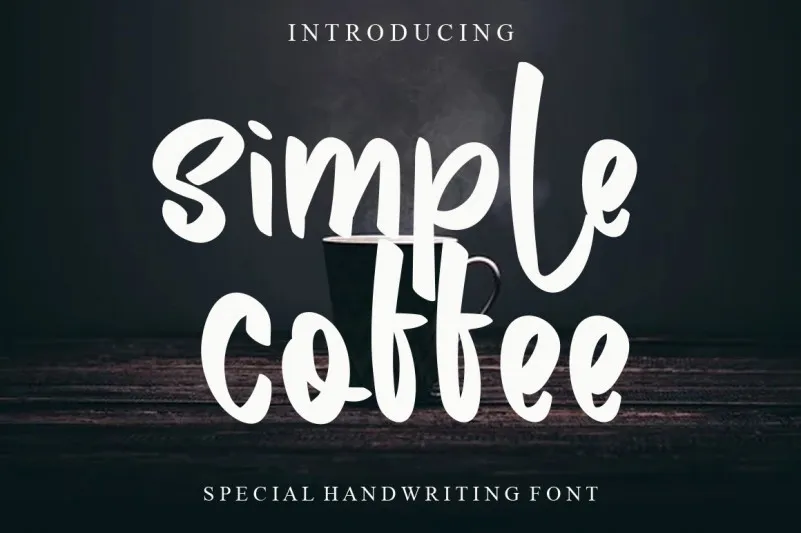
Esta é uma fonte a mão escrevendo, desenhada para designers que procuram algo fresco e divertido. Com um visual elegante e cíntica, ela promete dar seu projeto um toque único e moderno. Ideal para aqueles projetos criativos e inovadores onde você deseja destacar sua identidade visual com estilo. Composta por letras de uma escrita cursiva, essa fonte é perfeita para quem quer imprimir um tom pessoal e divertido em seus materiais digitais. Seja em postagens no Instagram ou cards personalizados, a fonte “Simple Coffee Font” é certamente uma escolha ótima para quem busca criatividade e estilo. Aproveite essa fonte levemente escrita de designer para enriquecer seus projetos.